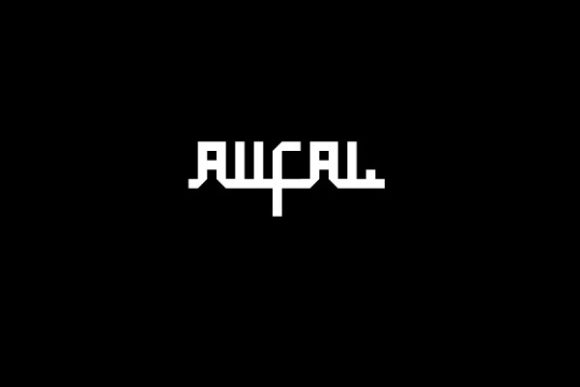
Fuente Aufal para titulares, carteles y proyectos de marca
Aufal es una fuente de exhibición moderna y con un diseño interesante que le da un toque único a cualquier proyecto. Perfecta para pósteres, folletos e impresiones, potencia la creatividad. Explora sus infinitas posibilidades y haz que tus diseños destaquen con la fuente Aufal.